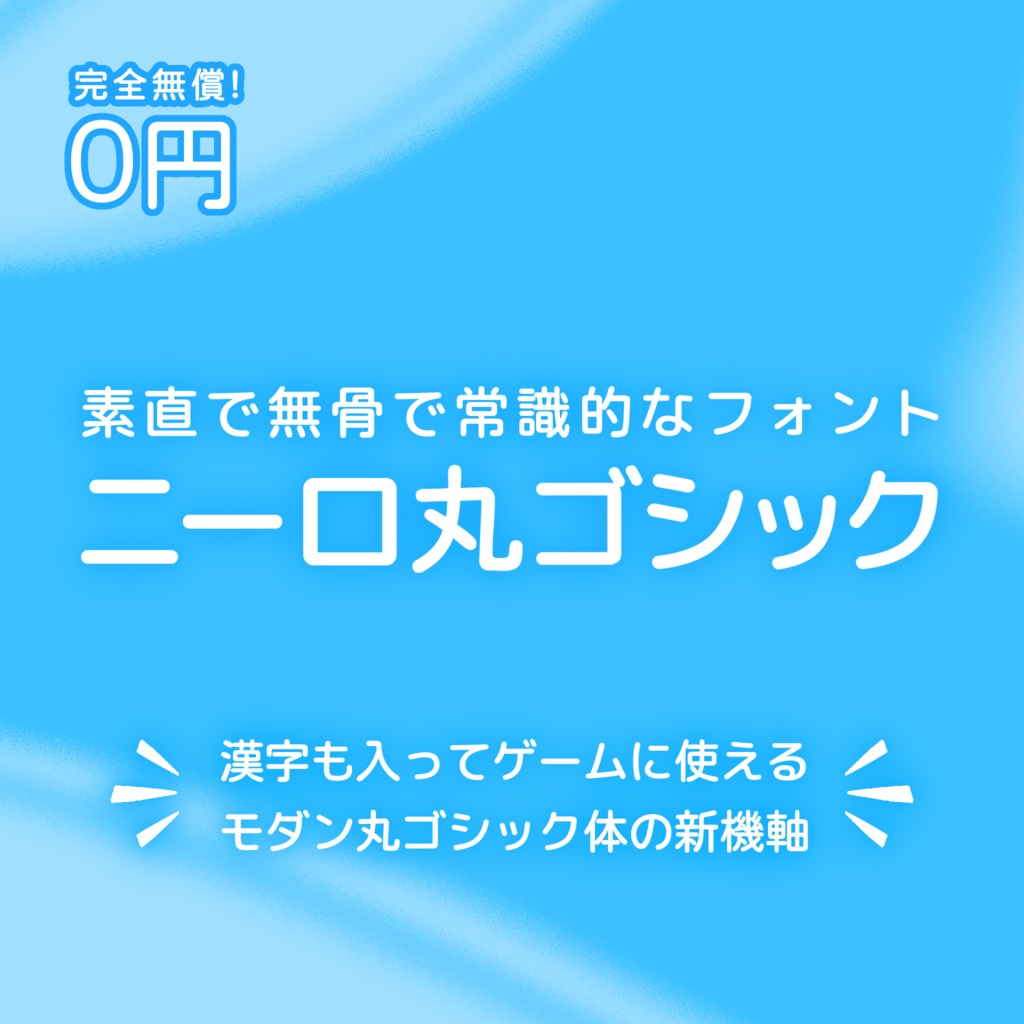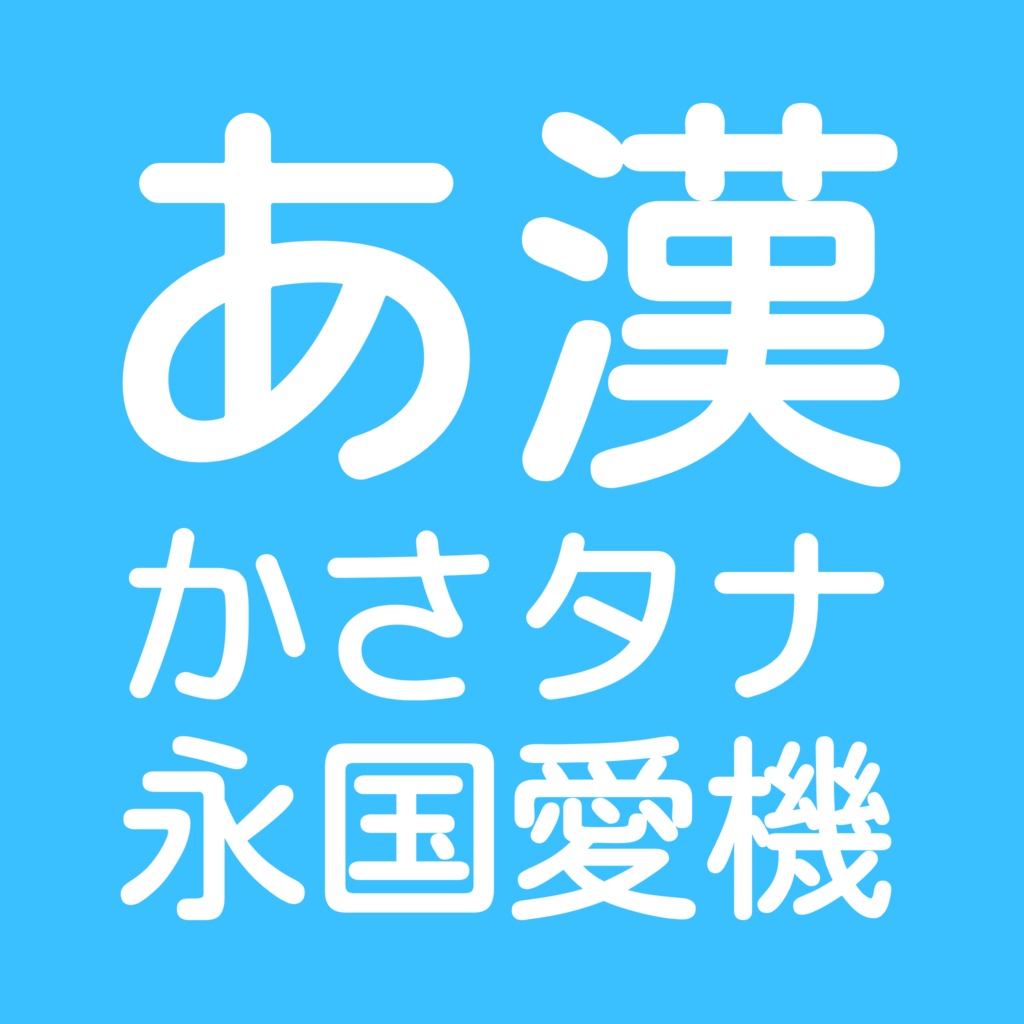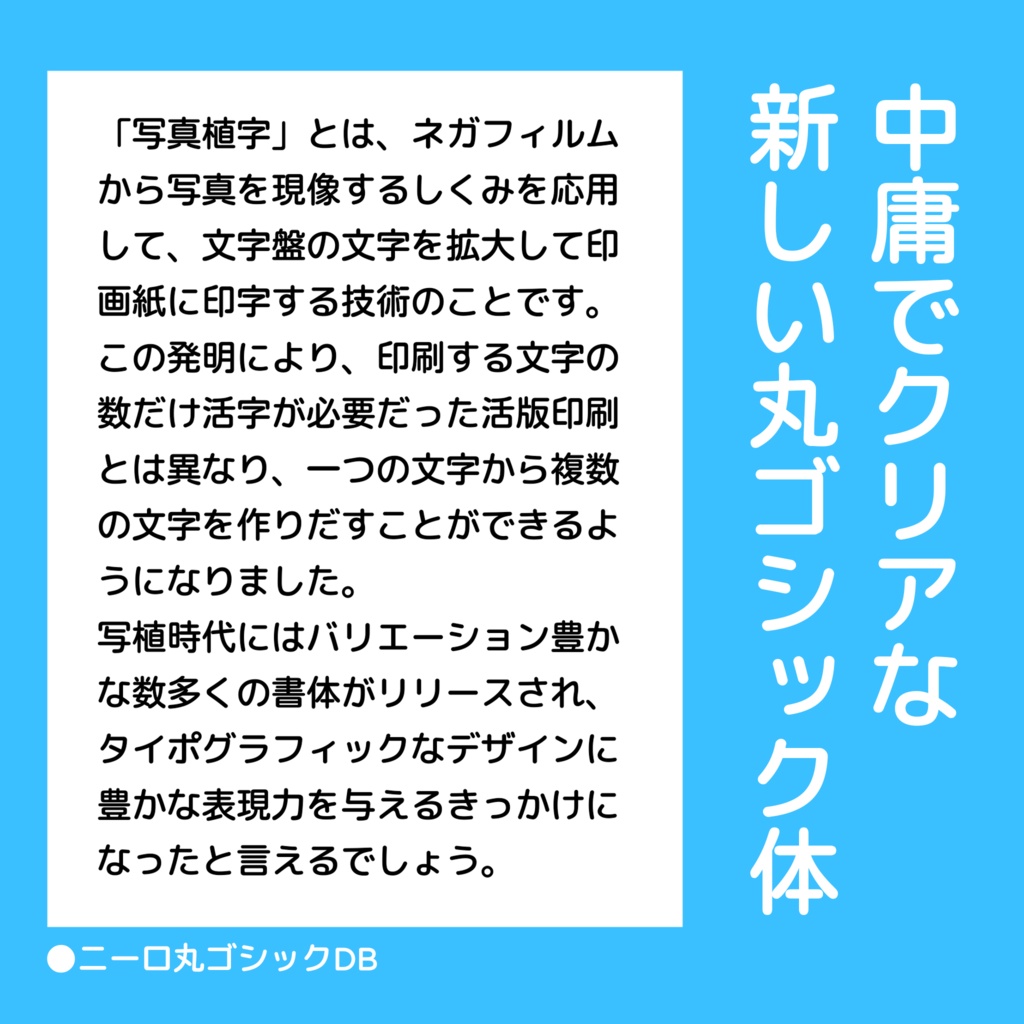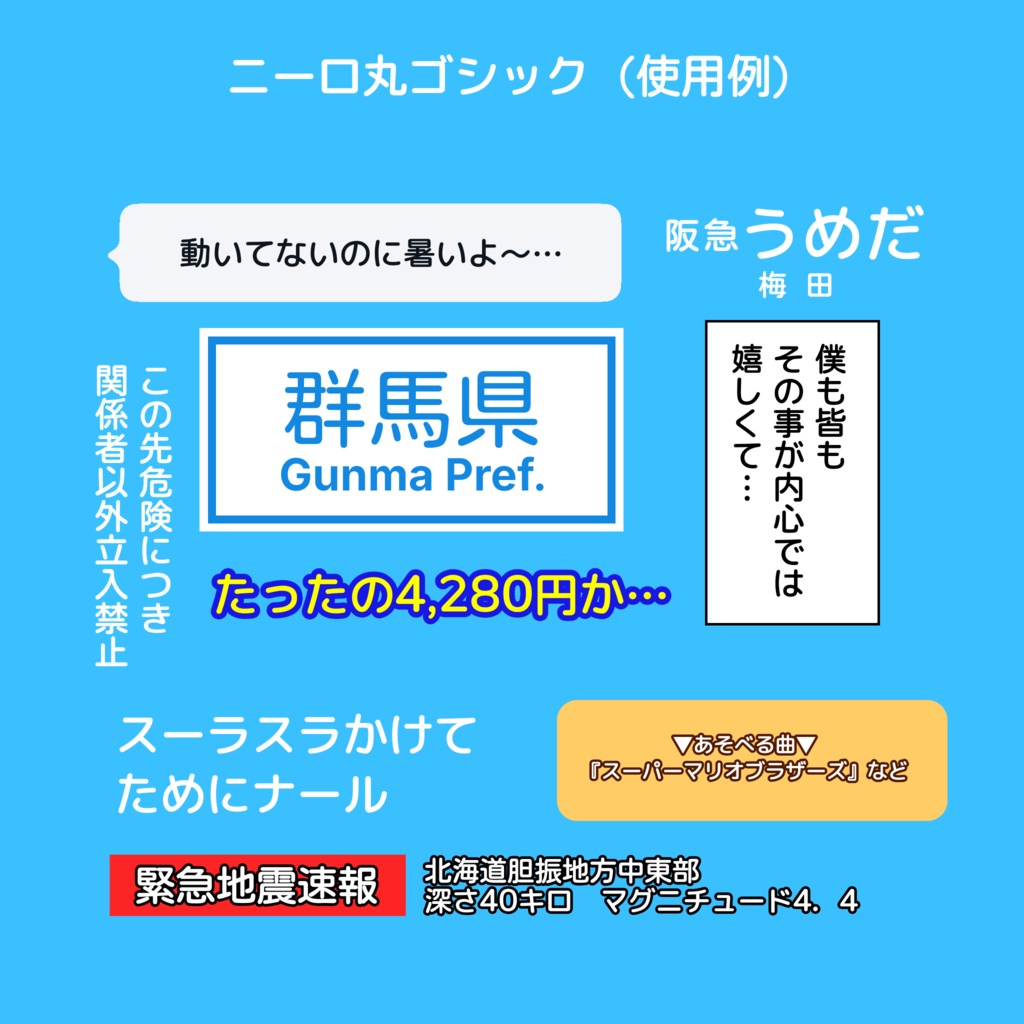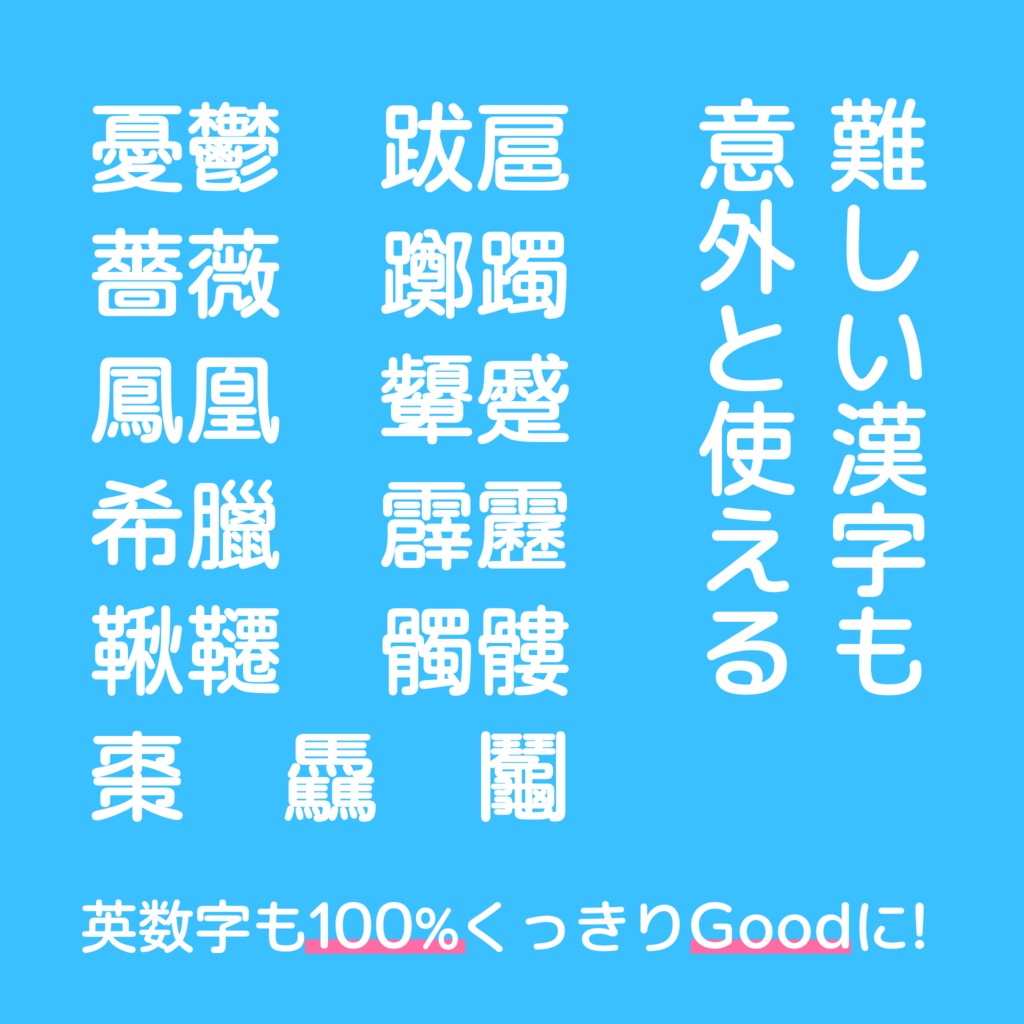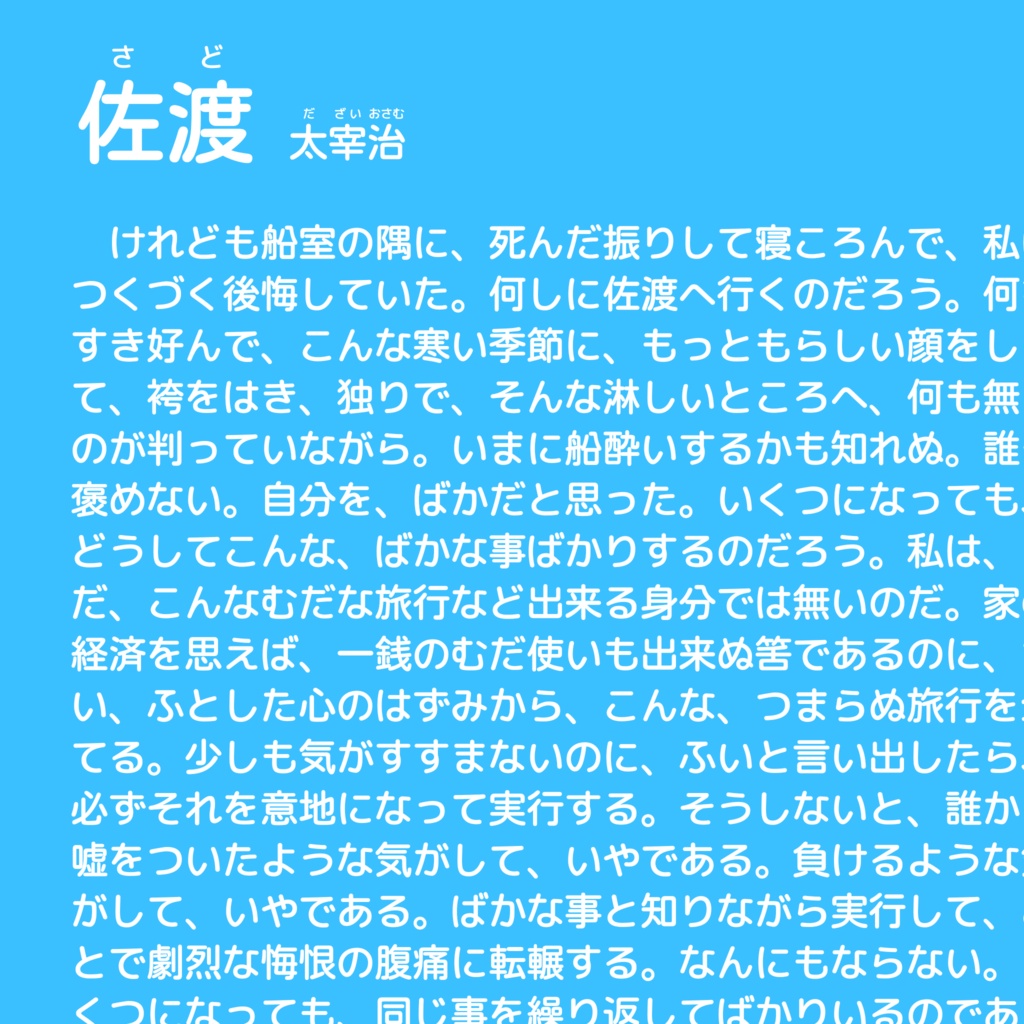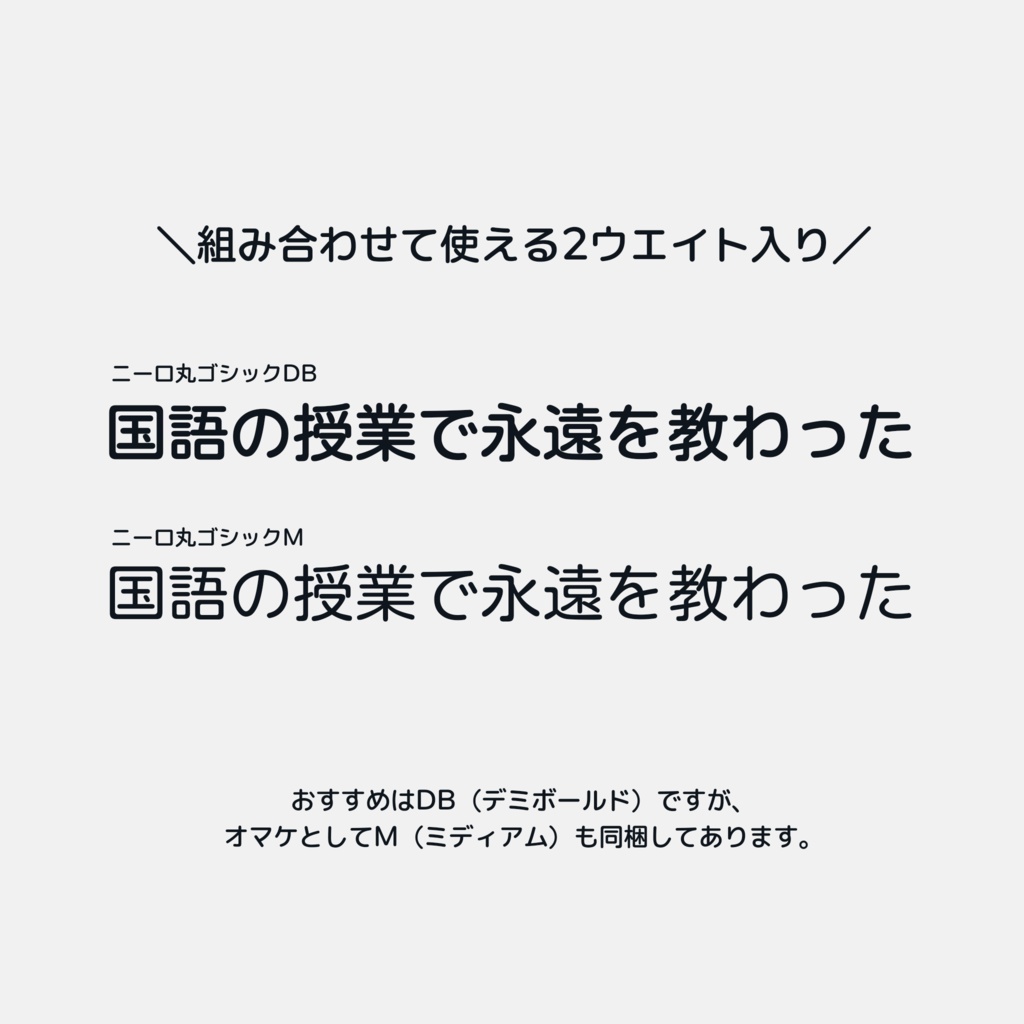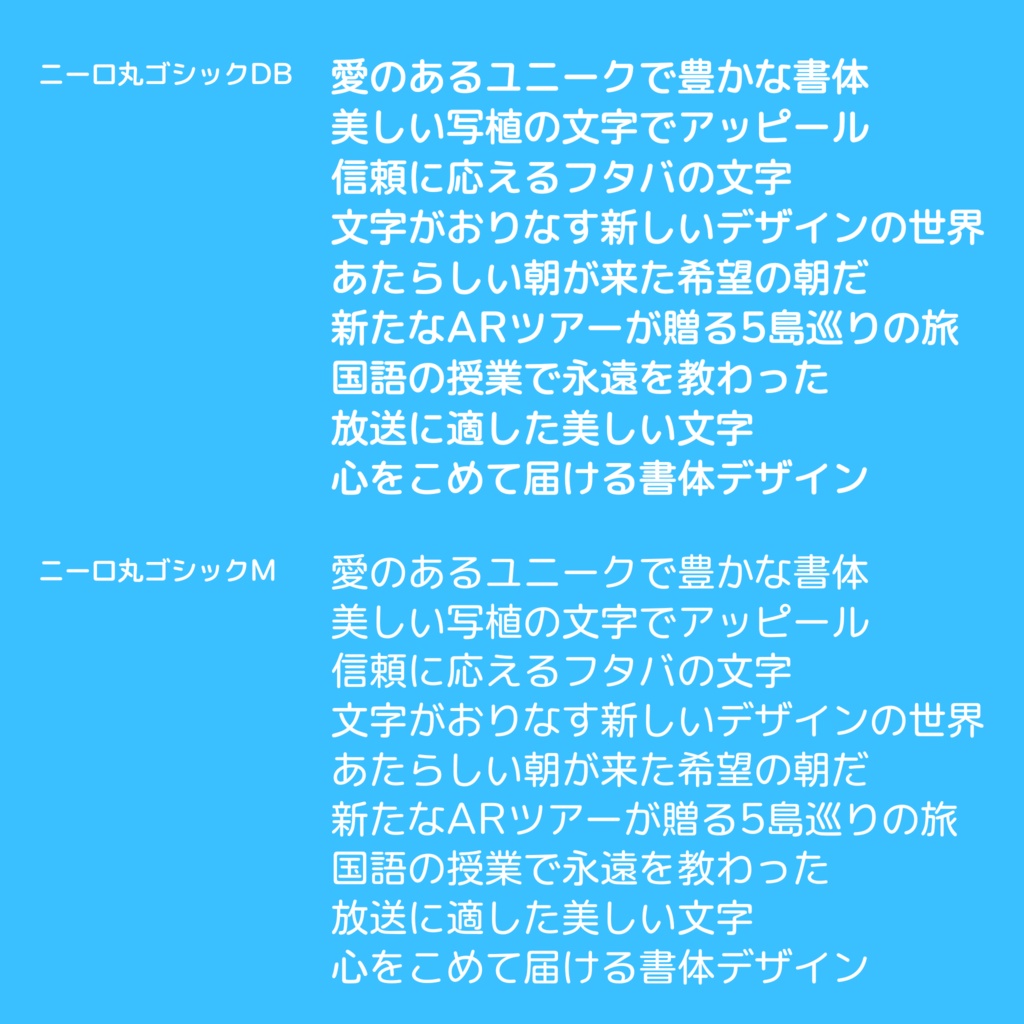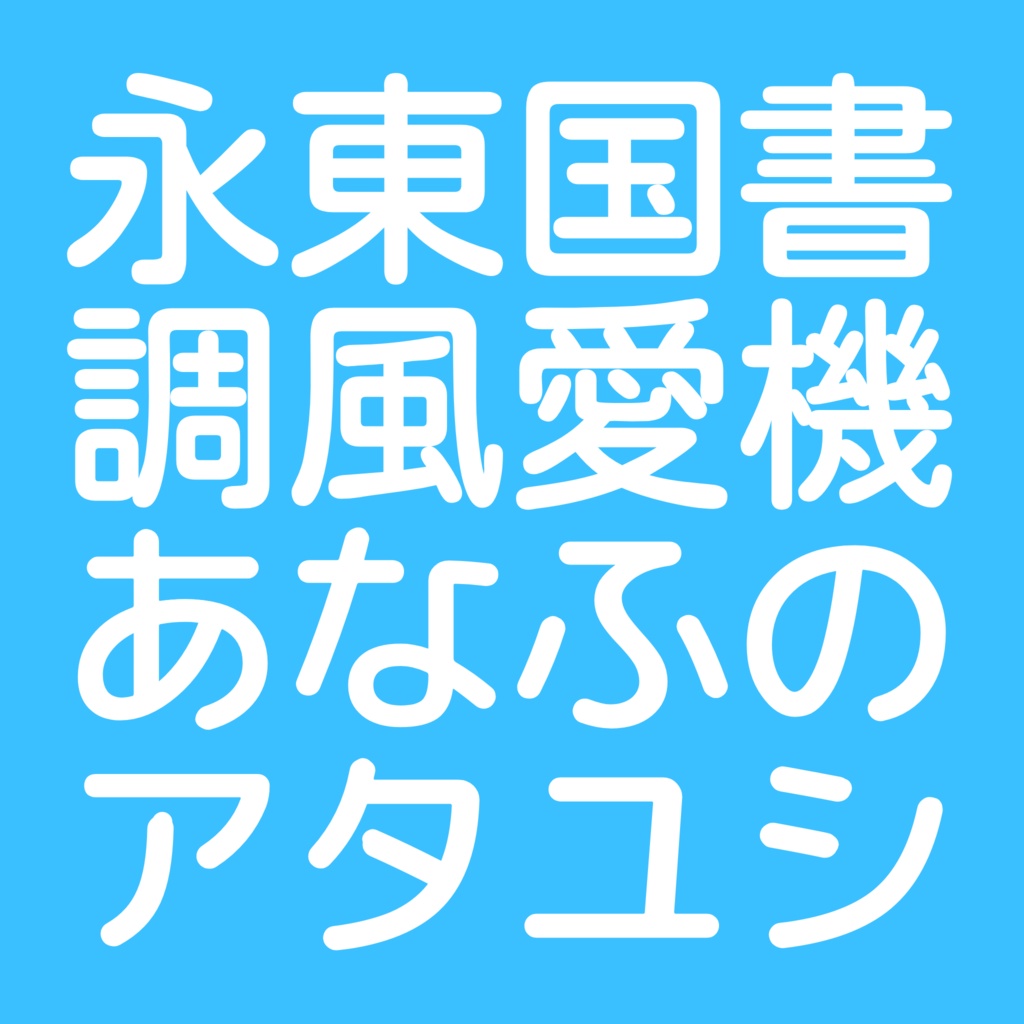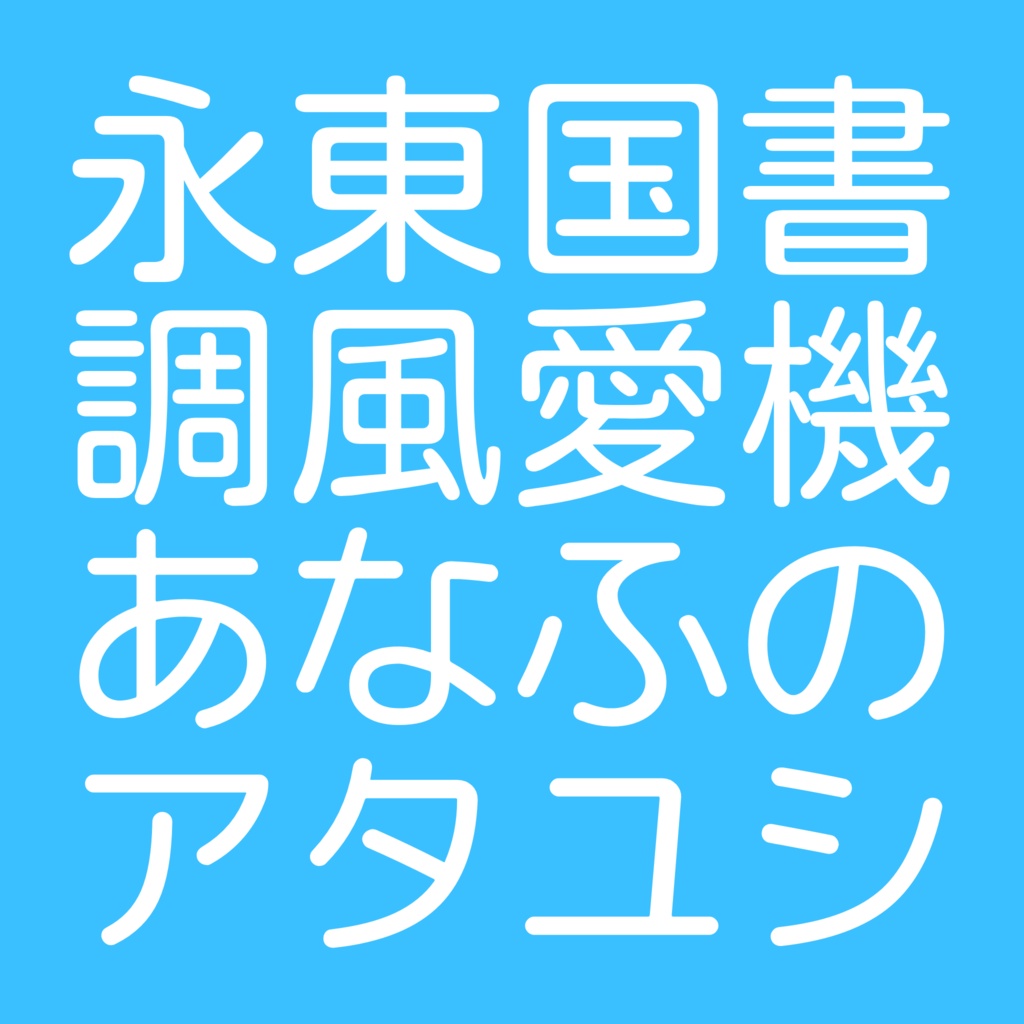
【フリーフォント】ニーロ丸ゴシック
個人・商用を問わず無料で利用できる、モダンな丸ゴシック体です。 印刷物、画像、映像、同人作品、ゲーム、アプリ、Webサイトなどにもご自由にお使いいただけます。 SIL Open Font License 1.1のもとで、改変・再配布も可能です。 詳しい条件は同梱のOFL-1.1.txtをご確認ください。 ■収録ウェイト - ニーロ丸ゴシック DB DemiBold相当 - ニーロ丸ゴシック M Medium相当 ■スペシャルサンクス - FakePearl / Chun yu Yao - 小杉丸ゴシック / The Kosugi Maru Project Authors - 自家製 Rounded M+ / M+ FONTS PROJECT - SN Pro / The SN Pro Project Authors, Supernotes, Tobias Whetton